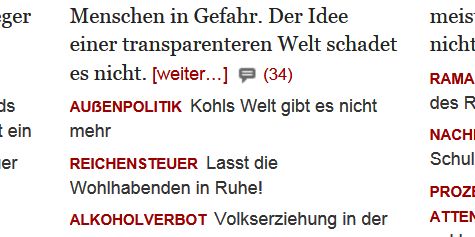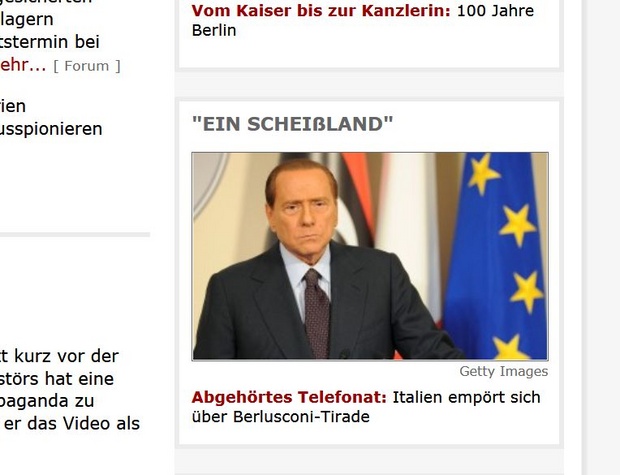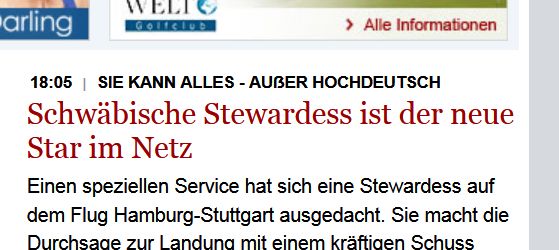
Browserunterstützung: ß als Kapitälchen und Großbuchstabe
Ein kurzer Test zeigt, dass mehrere Browser mit ß in den verschiedensten Konstellationen Probleme haben, besonders wenn @font-face ins Spiel kommt. Nicht nur Safari zickt, auch Opera und Chrome und Internet Explorer haben gleich mehrere Probleme. Firefox schneidet noch am besten ab.
In der Tat ein sehr seltsames Ergebnis. Dass Safari font-variant: small-caps; mit kleinem Eszett darstellt, hatten wir ja schon festgestellt.
Bei @font-face (ignorant of browser styles) habe ich in Firefox und Safari ein identisches (überraschendes Ergebnis):
small-caps wird mit Versaleszett dargestellt (huch!) und uppercase mit Doppel-S.
Echt, auch Firefox? Ich nehme an, auf’m Mac? Welche Browser-Version?
Firefox (3.6.13) ist bei mir – getestet in Linux und Windows Vista – der einzige Browser, der sich regelkonform konservativ verhält und aus ß (U+00DF) überhaupt kein großes Eszett machen will und bei Umwandlungen in Kapitälchen oder Versalien nur »SS« darstellt. Die einzige Ausnahme ist Testfall II.2 (ich habe die Testseite noch mal leicht erweitert), was aber nicht weiter verwunderlich ist, da dort die Kapitälchenversion der Libertine direkt eingebunden ist und ß (U+00DF) eben als verkleinertes ẞ dargestellt wird. Es findet aber keine Umwandlung U+00DF → U+1e9e statt.
Die Rückumwandlung U+1e9e → U+00DF funktioniert hier im FF auch wunderbar und regelkonform. Auch dort patzt z.B. Opera.
Schreib doch ruhig mal in jeder Zeile den CSS-Kode mit hin. Dann versteht man besser was passiert.
Und für die Klammer wäre schön, (Ausgangszeichen -> umgewandeltes Zeichen) zu zeigen, da ja nun nicht in allen Zeilen das ß im Quelltext steht.
Und zum Vergleich vielleicht noch einen Webfont ohne Versaleszett?
Schreib doch ruhig mal in jeder Zeile den CSS-Kode mit hin.
Weiß nicht … Da auch die geerbten Stile relevant sind, müsste ich wohl das gesamte Stylesheet replizieren. Das kostete nicht nur Platz, sondern wäre auch noch fehleranfällig. Ich denke mal, dass die Sache für Leute, die keine HTML-Quellen anschauen können, ohnehin kaum interessant sein dürfte. ;-)
Und für die Klammer wäre schön, (Ausgangszeichen -> umgewandeltes Zeichen) zu zeigen, da ja nun nicht in allen Zeilen das ß im Quelltext steht.
Und zum Vergleich vielleicht noch einen Webfont ohne Versaleszett?
So besser?
Ach ja, meine Vista-Screenshots (noch mit der alten Version ohne IM Fell und die Extra-ßs in Klammern) sind hier.
Gerade entdeckt:
funktioniert anscheinend nirgends. Extrem doof! :evil:
Ich denke mal, dass die Sache für Leute, die keine HTML-Quellen anschauen können, ohnehin kaum interessant sein dürfte. ;-)
Ich kann das ja, hab aber trotzdem Schwierigkeiten, mich da in jede Zeile neu reinzudenken. Und die Browser-Entwickler, die diese deutschen Besonderheiten nicht kennen, werden es umso schwerer haben.
Auf jeden Fall müssen wir da wohl ein paar Fehlerberichte einreichen. Und eine gute Demoseite kann da natürlich nicht schaden.
Das ß im Kapitälchensatz geht natürlich gar nicht und auch die teilweise unterschiedliche Behandlung von Small Caps und Versalsatz kann ja so nicht bleiben.
Wobei ich jetzt gar nicht wüsste, was man zum Thema Versaleszett empfehlen soll. So sehr ich damit sympathisiere, als Standard kann ich mir das noch nicht so richtig vorstellen. Geschweige denn, wenn dann z.B. das Kapitälchenversaleszett synthetisiert ist oder es aus einer anderen Schrift kommt, weil in der benutzten nicht vorhanden.
Andererseits könnte eine breite Browserunterstützung zur Verbreitung beitragen!
Ich fände auch hilfreich, den Code neben den Beispielen zu zeigen.
funktioniert anscheinend nirgends. Extrem doof! :evil:
Ja, das ist schade. Vermutlich handelt es sich dabei nicht um einen Browser-Bug, sondern um eine Konsequenz aus dem aktuellen CSS Fonts Module Level 3 (W3C Working Draft 18 June 2009). Dort stellt sich nämlich heraus, dass die in @font-face verwendeten Angaben «descriptor» heissen, im Unterschied zu den gewöhnlichen CSS-Bestimmungen, die «property» heissen.
Einige Angaben existieren zwar gleichlautend (aber mit gewissen Unterschieden!) sowohl als «descriptor» als auch als «property», nämlich [i]font-family[/i], [i]font-style[/i], [i]font-weight[/i] und [i]font-stretch[/i]. Andere Angaben hingegen gibt es nur als «property», aber nicht als «descriptor», eben beispielsweise [i]font-variant[/i].
Das W3C scheint aber die Angelegenheit am Verbessern zu sein, vgl. CSS Fonts Module Level 3 (Editor's Draft).
Man kann wohl also sagen, dass wenigstens an Firefox im Rahmen des derzeitigen Stands von CSS3 nichts auszusetzen ist.
Wobei ich jetzt gar nicht wüsste, was man zum Thema Versaleszett empfehlen soll. So sehr ich damit sympathisiere, als Standard kann ich mir das noch nicht so richtig vorstellen. Geschweige denn, wenn dann z.B. das Kapitälchenversaleszett synthetisiert ist oder es aus einer anderen Schrift kommt, weil in der benutzten nicht vorhanden.
Die jeweilige Darstellung hängt also alleine von der Schrift ab. Wünschenswert wäre wohl, dass man in einer Schrift aussuchen könnte, ob der Buchstabe ß in Kapitälchen als SS oder als dargestellt werden soll. Ich bin mir nicht sicher, wie sich schriftprogrammiertechnisch bewerkstelligen liesse. Auf alle Fälle hilft hier das grosse ẞ für Kapitälchen nicht weiter, da es ja um die Darstellung des Buchstabens ß geht. Naheliegend wären wohl optional einschaltbare Features wie cv01. Die Schrift würde dann per Default entweder die erste oder die zweite Interpretation anwenden, aber über das optionale Feature könnte man den Default ändern.